手写体是设计师和普通用户都非常喜欢用来表达自然、温暖和创意的一种字体风格。互联网越来越娱乐化,所以轻松的手写体是很多用户非常喜欢的一种字体,作为设计师的我们,也要更多的了解和使用手写体。本文就给大家汇总 20 款手写体大全,包含了 10 款免费手写体和 10 款付费的手写体。
一、什么是手写体?
手写体就是模仿人们手写文字的字体。不同于传统的黑体、宋体等机械感强烈、线条规整的字体,手写体的线条更具流动感,形态更加随意和自然,呈现出一种温馨、亲切甚至带有个性化的感觉。它可以是潇洒的草书,也可以是整齐的连笔印刷体,风格丰富多样。
手写体的设计灵感来源于人们的日常书写动作和笔迹,因而每一种手写体都带有设计师独特的情感和风格烙印。它不只是字体,更像是一种情感的传递,让文字更加的灵动和活泼。
二、手写体的使用场景
1、品牌设计
文创、时尚、餐饮等品牌比较适合用手写体来塑造亲切自然的品牌形象,比如咖啡馆菜单、手工艺品包装、化妆品品牌LOGO等。
2、邀请函和贺卡
婚礼邀请函、节日贺卡、生日卡片等常用手写体来营造温馨浪漫的氛围。
3、社交媒体和内容创作
手写体在微信公众号、抖音等短视频等多媒体的封面中经常使用,能够快速吸引眼球,提升内容的亲和力。
4、儿童教育和书籍
手写体中那种童真和活泼的感觉,十分适合儿童读物、教育资料的设计,能帮助孩子们更有兴趣去阅读。
5、艺术与创意设计
手写体为创意海报、艺术展览、DIY手工制作等提供了无限的创作空间,表现力丰富。
沐瑶软笔手写体
沐瑶软笔手写体呈现出一种柔和的书写风格,仿佛用软笔书写而成,字形优雅流畅。沐瑶软笔手写体适合用于各种温馨、文艺的设计场景,如邀请函、贺卡等,我在邀请函的设计时,经常使用沐瑶软笔手写体。
演示悠然小楷
演示悠然小楷是一种结构紧凑、笔画清晰的小楷字体,体现出传统书法的韵味。适合用于正式场合的文书、证书等,表现出严谨和优雅的风格,同时其字形清晰,便于阅读。
钟齐志莽行书
钟齐志莽行书是一种具有动感和个性的行书字体,笔画流畅而富有力度。适合用于艺术作品、书法展示等场合,能够彰显作者的个性与风格,具有较高的艺术欣赏价值。
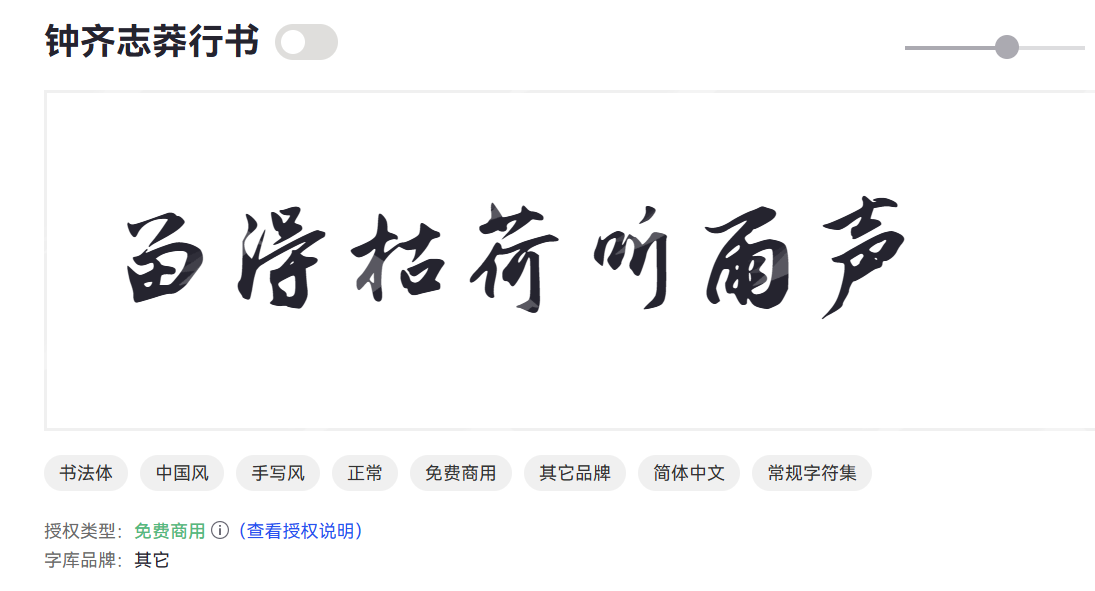
Aa剑豪体
Aa剑豪体是一种充满力量感的字体,线条干练,常用于标题和强调内容。适合用于游戏、武侠主题的设计,能够吸引眼球,传递出活力与激情的信息。在做仙剑的营销海报时,就用的这款字体,非常适合武侠题材。
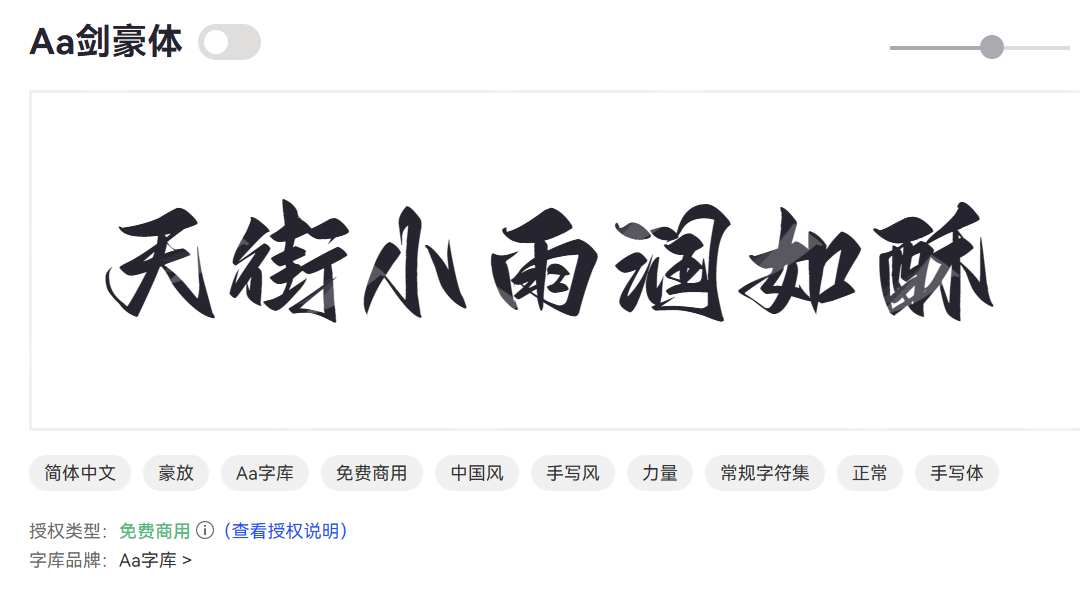
杨任东竹石体
杨任东竹石体字形自然,带有竹子的清秀气息,浑然天成。适合用于自然、生态相关的设计,给人以清新、舒适的视觉感受,体现出和谐之美。
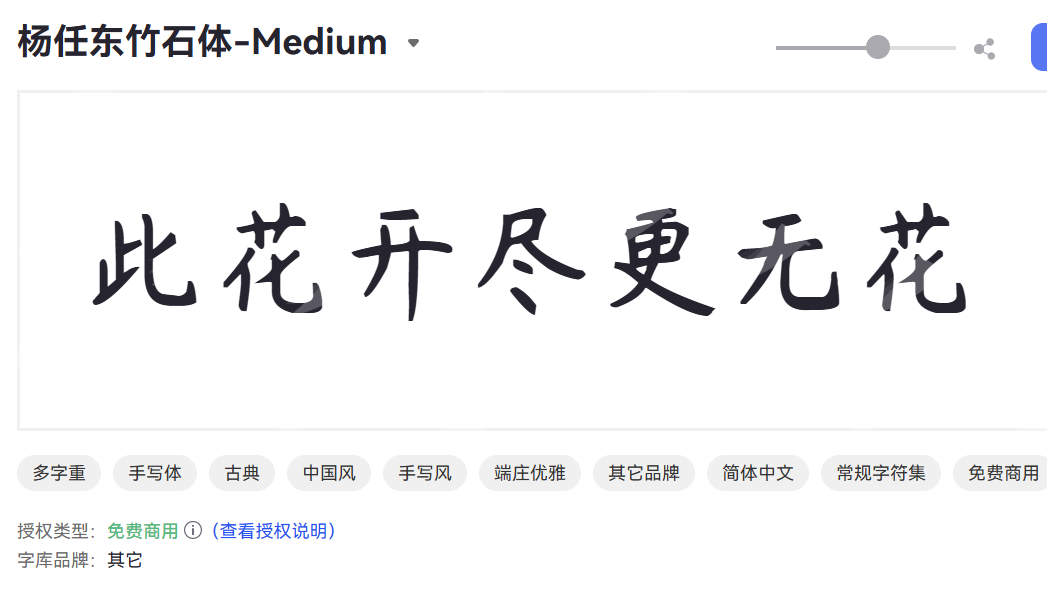
鸿雷行书简体
鸿雷行书简体字形优美,笔画流畅,具备行书的速度感与艺术性。鸿雷行书简体适合用于书信、博客等非正式场合,能够传递出一种轻松自在的氛围。
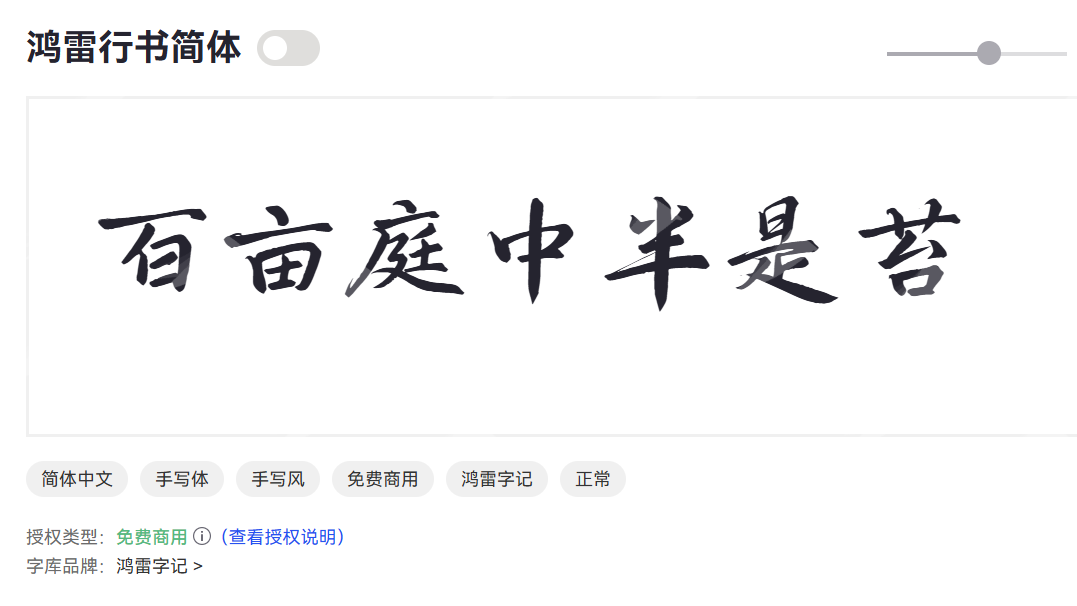
点字浅夏体
点字浅夏体是一种清新自然的字体,适合展现夏日的生机与活力。点字浅夏体适合用于青春、活泼的设计,能够引起年轻人的共鸣,展现出一种向上的精神面貌。
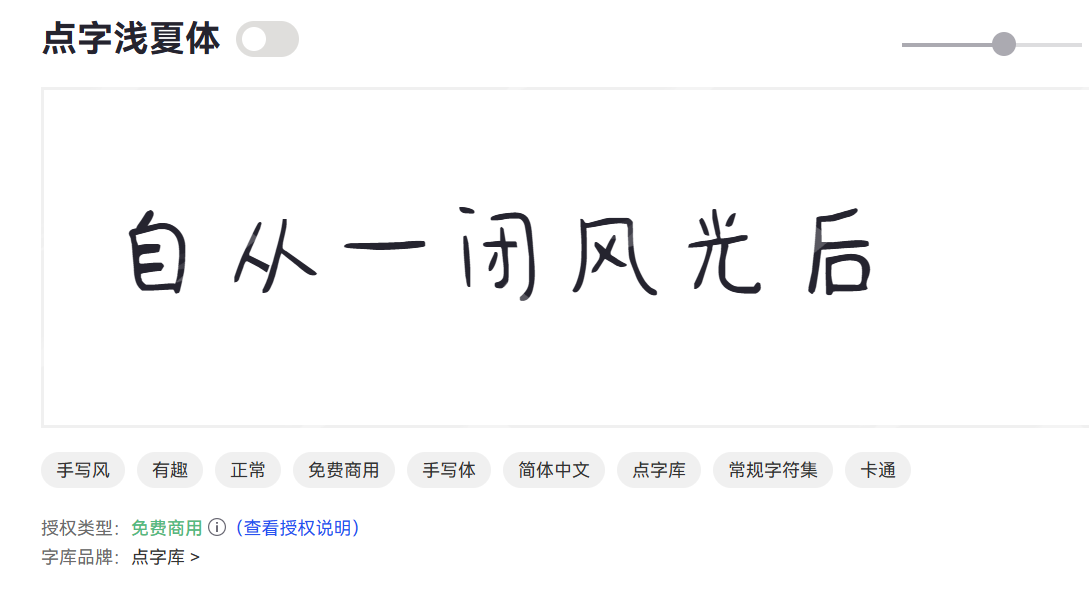
鸿雷板书简体
鸿雷板书简体字体结构简单,易于辨识,具有很强的实用性。适合用于教学、演示等场合,能够清晰地传达信息,适合大众阅读。建议在教学课件,可以使用这款字体。
庞门正道粗书体
庞门正道粗书体字形饱满,线条粗壮,给人以强烈的视觉冲击。庞门正道粗书体适合用于海报、广告等需要强调的场合,能够有效吸引观众的注意力。海报设计的时候建议可以试试。
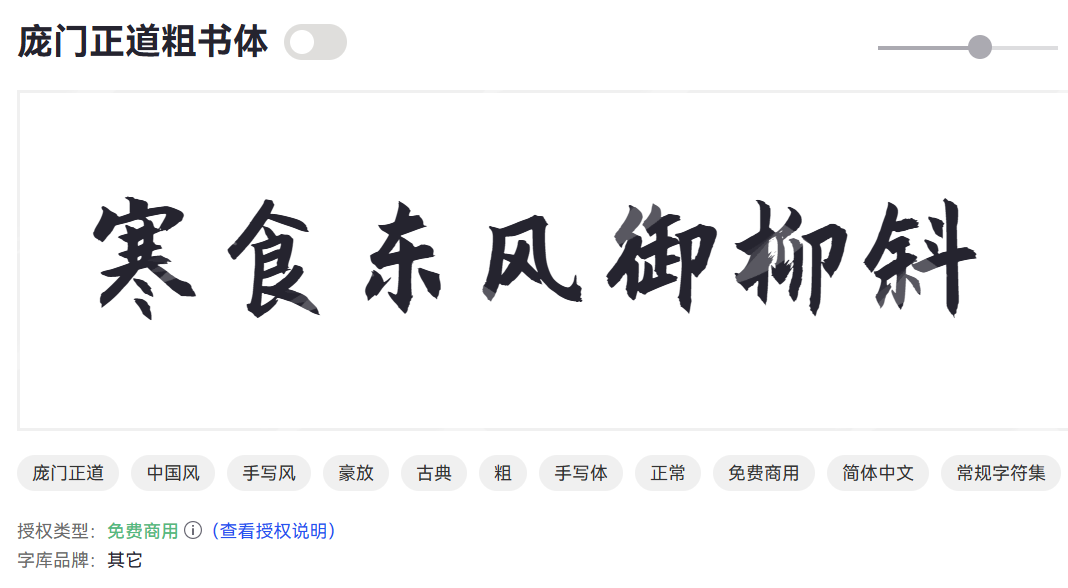
龚帆免费体
龚帆免费体是一种简单易读的字体,结构规整,易于使用。适合用于日常文档、简报等,具备很好的通用性,方便用户在多种设计中应用。
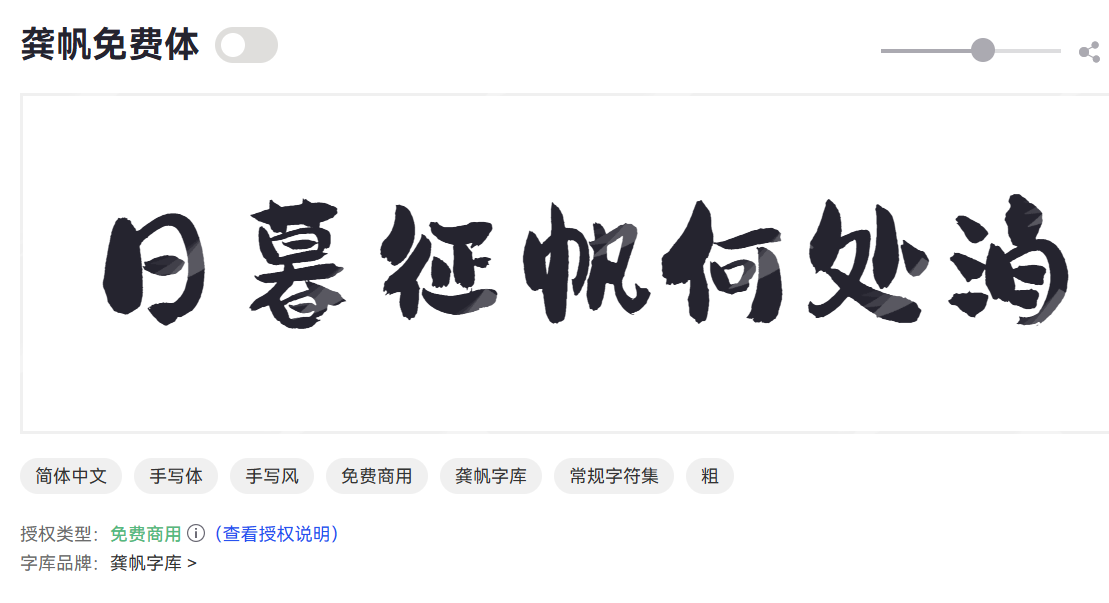
演示镇魂行楷
演示镇魂行楷是一种兼具行书与楷书特点的字体,字形优雅,充满力量。适合用于文艺作品、书法作品展示,能够传达出深邃的文化底蕴与艺术感。
演示新手书
演示新手书是一种简单流畅的字体,适合初学者使用。适合用于教育、学习相关的内容,能够帮助读者更好地理解和学习。
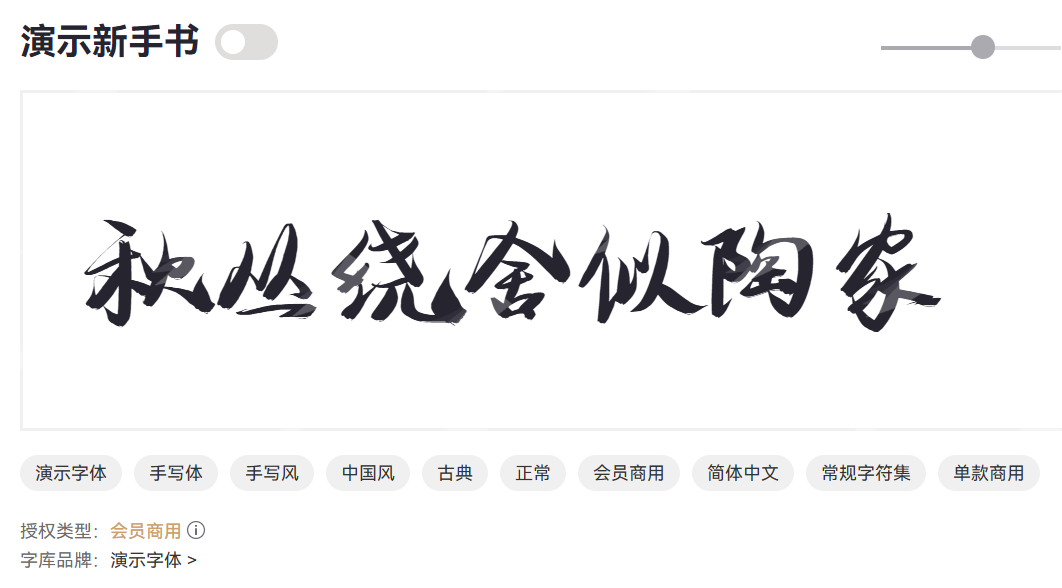
点字混元体
点字混元体是一种融合多种风格的字体,独特而富有个性。点字混元体适合用于创意设计、品牌推广等,能够展现出独特的品牌形象。
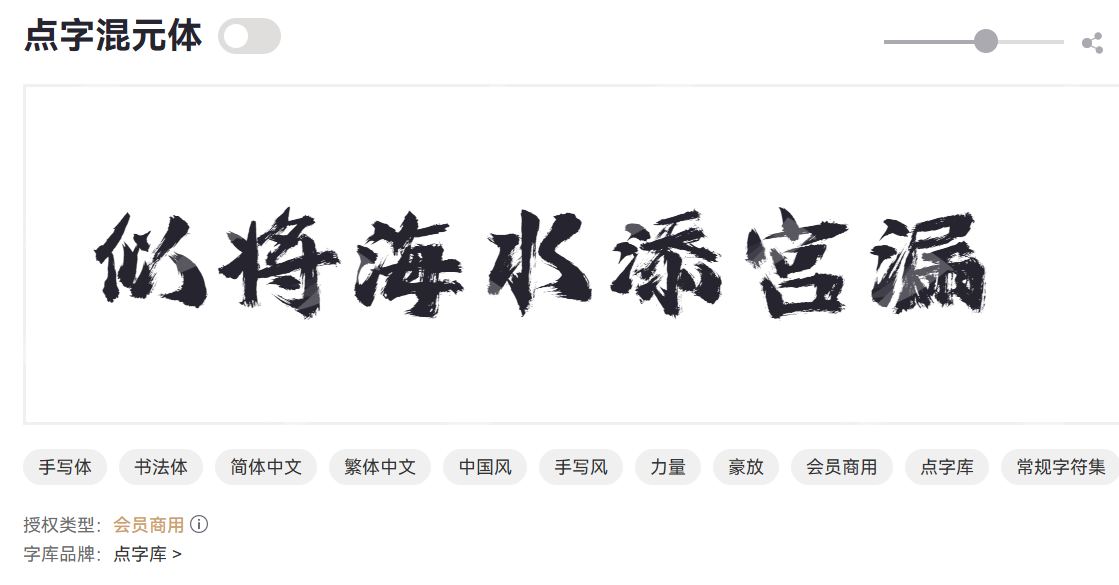
点字浩魂
点字浩魂浩魂字体线条流畅,整体感觉灵动而有力量。点字浩魂适合用于诗歌、散文等文学作品,能够增强文本的情感表达。
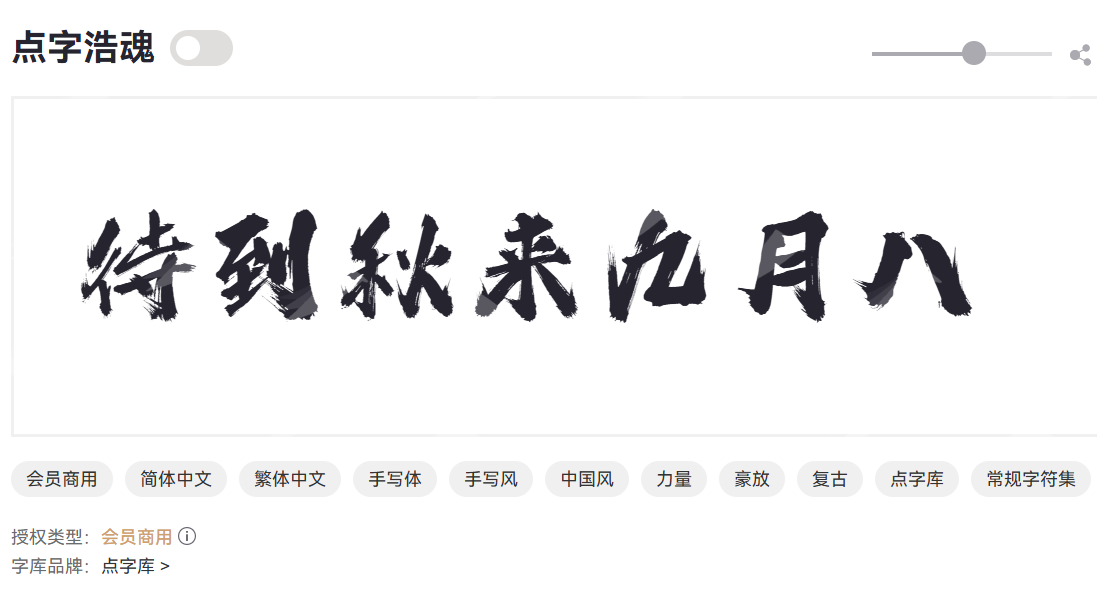
叶根友古刻体是一种有古典韵味的字体,结构复古,显示书法的传统美感。叶根友古刻体适合用于传统文化相关的设计,如书法展、文物介绍等,能够传递出深厚的文化内涵。
点字龙飞正楷
点字龙飞正楷字形规整,笔画清晰,具有很好的可读性。点字龙飞正楷适合用于正式文件、公告等场合,能够展现出严谨和专业的形象。
汉呈王世李行书
汉呈王世李行书字体流畅,具有行书的轻盈感。适合用于艺术创作、书信交流,能够展现出书写者的个性与情感。如果做一些艺术类的设计,可以使用这款字体。
汉呈王天喜榜书
汉呈王天喜榜书字形大气,笔画粗犷有力,适合用于标语和标题。适合用于宣传、展示等需要引起注意的场合,能够传达出一种激昂的气氛。在很多需要特别突出标题的时候,我喜欢使用这款字体。
点字物语字体设计灵动,富有故事感,适合表达情感和故事。点字物语适合用于小说、故事书封面,能够吸引读者的注意力,激发阅读兴趣。一些短视频的封面也可以尝试。
叶根友离贤行书
叶根友离贤行书字形优雅,富有动感,适合用于艺术作品和个人书信。叶根友离贤行书能够展现书法的独特魅力,适合于推广传统文化相关的活动。